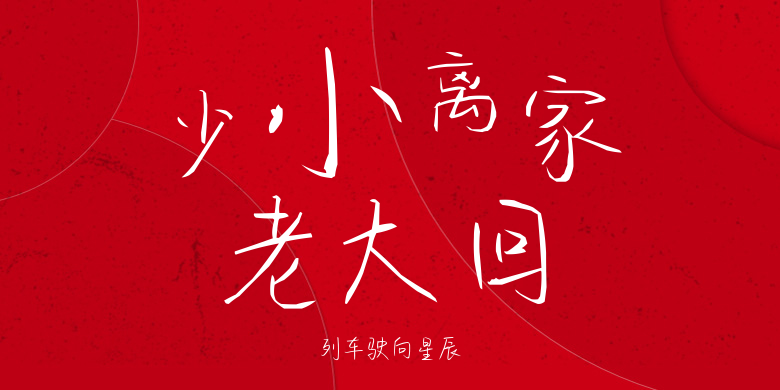
列车驶向星辰
列车驶向星辰,这款字体结构工整、笔画清晰,兼顾美观与易读性,适用于标题、正文、海报、包装、LOGO 等多种场景。字形优雅稳定,风格百搭耐看,适配日常排版与创意设计,让文字呈现更舒适、更具质感。列车驶向星辰一笔一画,皆是细节,以均衡的比例、流畅的线条打造舒适视觉体验,字形端正大气,风格简约现代。无论是商业设计、品牌宣传还是日常排版,都能轻松驾驭,让文字更有格调与力量。列车驶向星辰字体下载。